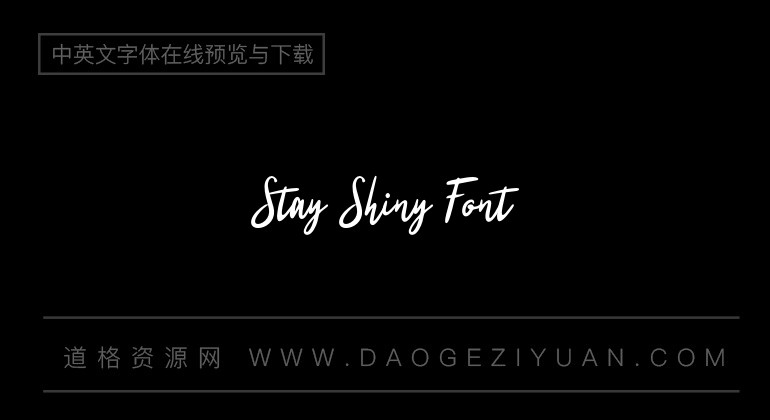
Stay Shiny Font 是一种流行的手写风格字体,具有光泽感和现代感。这个字体是由设计师 Mats-Peter Forss 创造的,他的设计风格常常融合了手写艺术和现代设计风格。 Stay Shiny Font 的字母形状流畅、简单,同时具有创意感。每个字母都似乎是由一个流畅的线条组成的,使得这个字体显得非常的光滑和优美,从而使得这种字体在品牌、广告和海报等设计领域中广泛使用。 该字体具有多个不同的样式和变体,包括粗体、斜体、正常和轻体,可以根据不同的需要选用不同的样式。它同时支持多种语言和字符集,如英文、西班牙语和法语等。 总之,Stay Shiny Font 是一种极具吸引力和现代感的手写字体,适用于多种设计领域,是一种非常流行的艺术字体。内容介绍
Stay Shiny Font是一款非常不错的手写艺术字体,具有很好的视觉感,适合于文化类的宣传设计、商业类品牌的广告和产品包装设计以及个性化文字排版等较多场景。